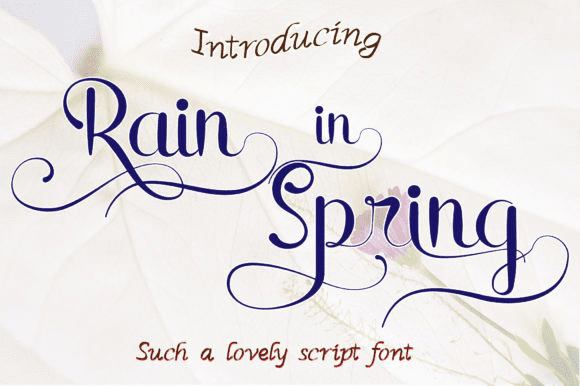
Название: Rain in Spring Font
Rain in Spring - это стильный современный шрифт, который подходит для брендинга, подписи, приглашения на свадьбу, продвижения, упаковки продукции и других нужд. Этот потрясающий рукописный шрифт - стильная дань уважения классической каллиграфии. Он поднимет широкий спектр дизайнерских проектов на самый высокий уровень.
Название: Rain in Spring Font
Rain in Spring - это стильный современный шрифт, который подходит для брендинга, подписи, приглашения на свадьбу, продвижения, упаковки продукции и других нужд. Этот потрясающий рукописный шрифт - стильная дань уважения классической каллиграфии. Он поднимет широкий спектр дизайнерских проектов на самый высокий уровень.